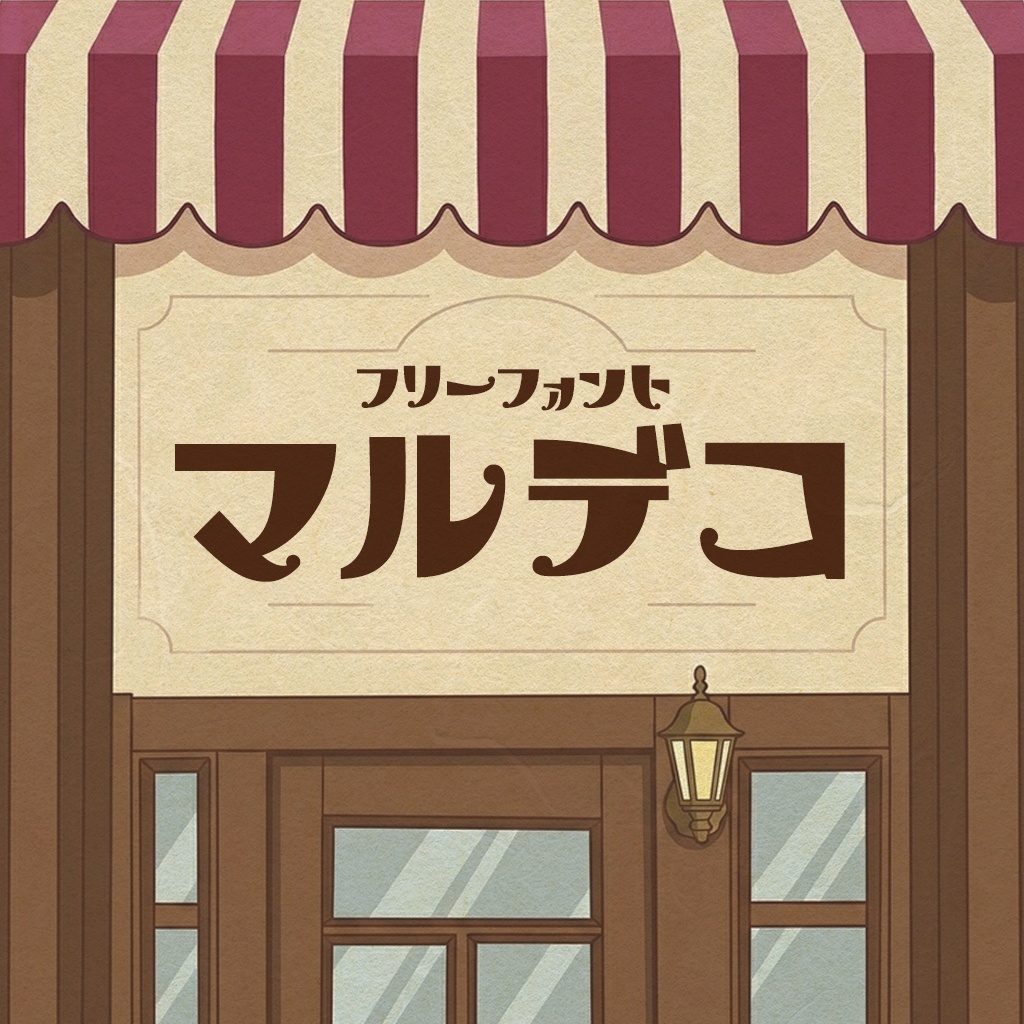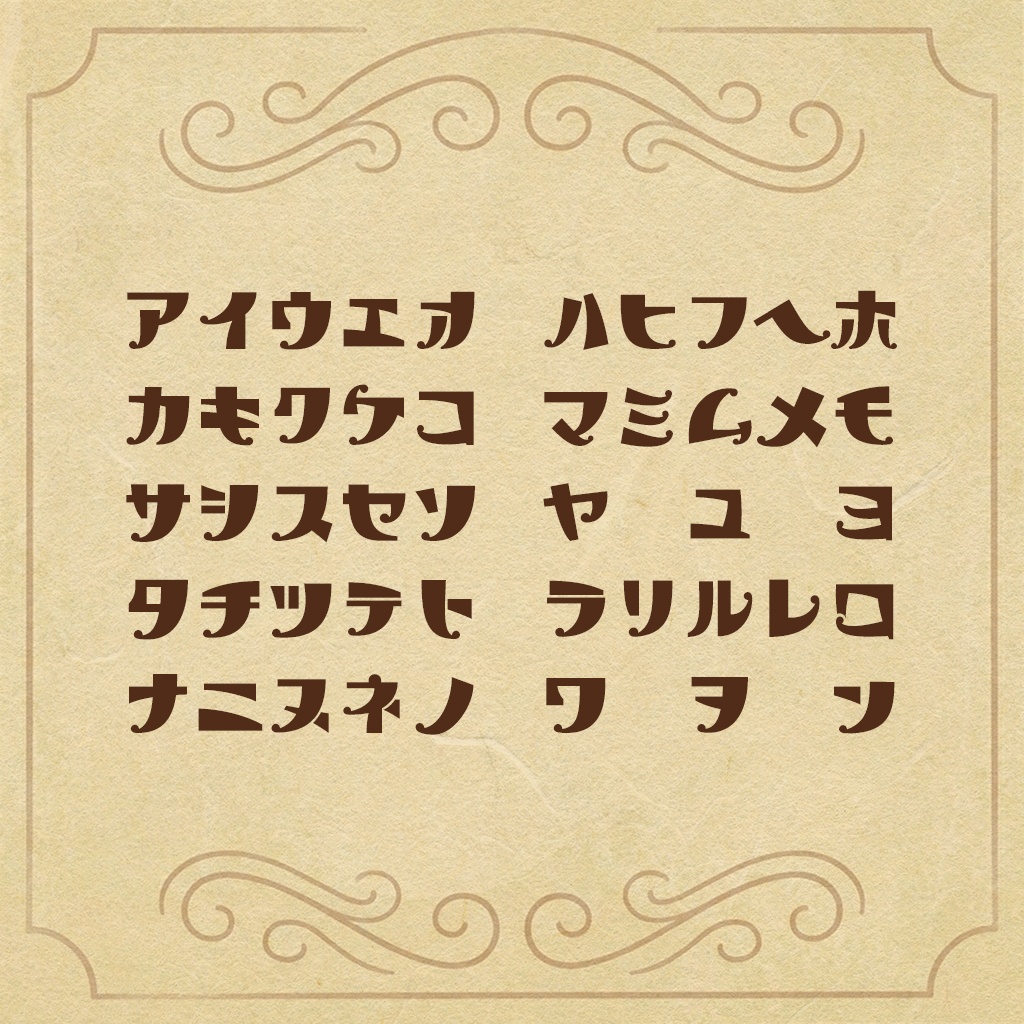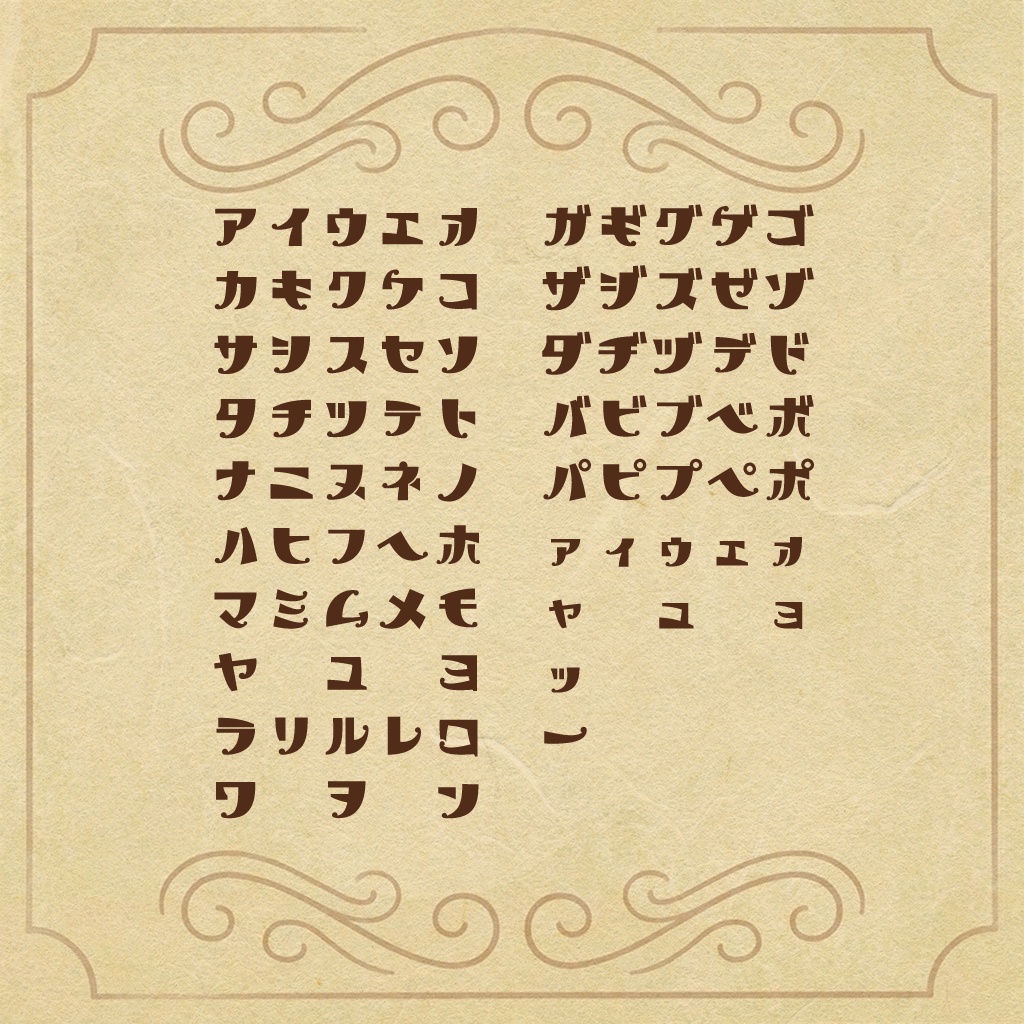
【フリーフォント】マルデコ
マルデコは昔ながらのクリーニング屋や美容室の看板文字をイメージした、丸みのあるレトロな日本語フォントです。 やさしく親しみやすい印象なので、同人誌やZINE、配信画面などにご使用いただける、カジュアルなデザインに適しています。 フォント形式:OpenTypeフォント 収録文字数:カタカナ102文字 ※後日アップデートでひらがなを追加予定 <作者からのコメント> 反応が良ければ収録文字数を増やすので、ぜひスキをしていただけると嬉しいです! また、使用報告も大歓迎です。作者のモチベが上がるので、ぜひお待ちしております!